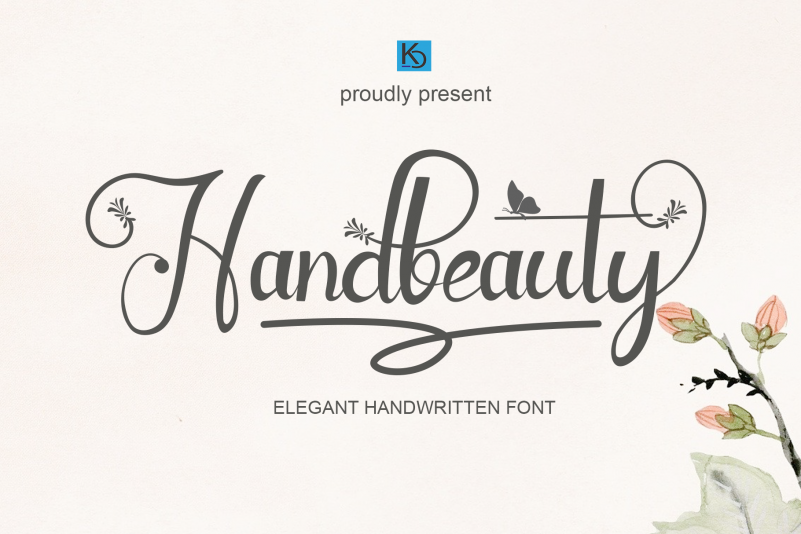
Handbeauty Font – Fonte Grátis
Handbeauty Font
A fonte Handbeauty é uma escolha perfeita para aqueles que valorizam delicadeza e elegância na tipografia. Com sua aparência fresca e suave, essa fonte de script está certa para iluminar qualquer projeto gráfico. Seus traços finos criam um efeito atraente e elegante, tornando-a uma opção irresistível para designers que desejam dar vida aos seus projetos. Independente do tipo de design ou mídia que você deseja incorporar essa fonte, ela será certamente uma peça-chave para criar designs impecáveis e surpreendentes. Seu uso irá conquistar qualquer espaço onde for aplicado, seja em logotipos, anúncios ou artes digitais. Aproveite a versatilidade desta fonte de script, uma delícia para o seu trabalho visual.